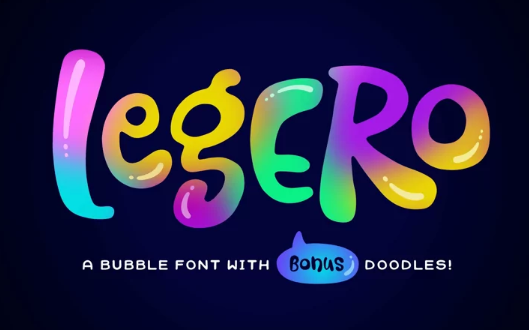
Legero - это веселый ретро-шрифт в пузырьковом стиле, который выпускается как в твердом, так и в блестящем вариантах. Он также поставляется с полным набором альтернативных символов, которые можно смешивать и сочетать, придавая своим проектам уникальность. Бонусные бесплатные материалы включают 52 рисунка на музыкальную тему, которые можно получить с помощью заглавных и строчных букв шрифта Legero Doodles, а также 6 абстрактных фонов, которые отлично подходят в качестве масок для создания рисунков, как на скриншотах.